In diesem Tutorial möchte ich den einfachen, aber sehr kreativen Effekt des Stickmusters entlang von Buchstaben erklären. Dazu zeige ich, wie für das Stickmuster eine Pinselvorgabe erstellt und diese als Stickmuster eingesetzt wird. Als zusätzlichen Mehrwert zeige ich, wie eine Jeanstextur in wenigen Schritten entstehen kann, die dann als Buchstabenmuster genutzt wird.
Vorbemerkung:
Damit das Tutorial nicht einfach nur nachgemacht wird, zeige ich als zusätzlichen Mehrwert, wie Pinsel und Jeanstextur selbst erstellt werden können.
Mein Dokument hat die Größe 800 x 600 Pixel.
Damit die Stofftextur einen gelben Farbton erhält, erstelle ich eine Einstellungsebene Farbton/Sättigung mit den Werten:
• Farbton: -180
• Sättigung: -42
• Helligkeit: +14
Mit einer 200-Punkt-Army Expanded schreibe ich die Buchstaben PSD in schwarzer Farbe in mein Dokument.
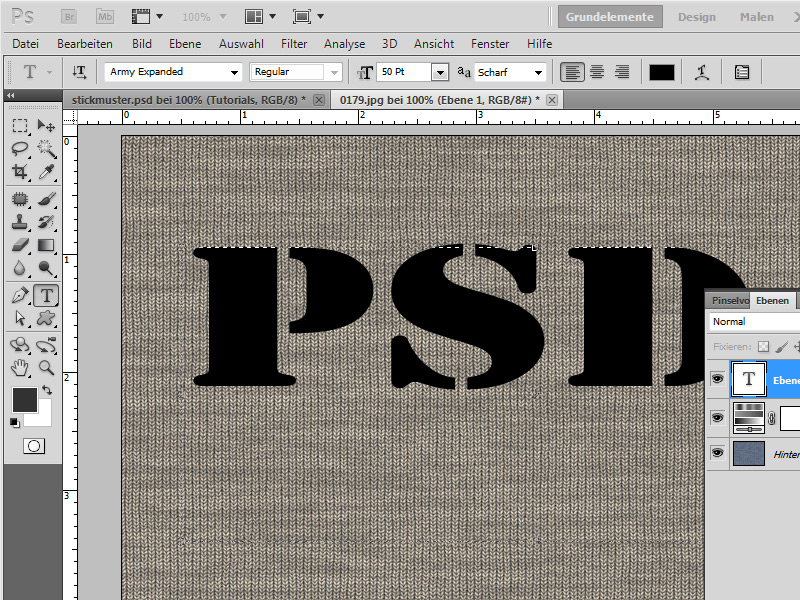
Mit Strg und Klick auf die Ebenenminiatur meiner Textebene wähle ich die Buchstaben aus. Nun wähle ich das Pfade-Bedienfeld und klicke dort auf das Icon Arbeitspfad aus Auswahl erstellen.
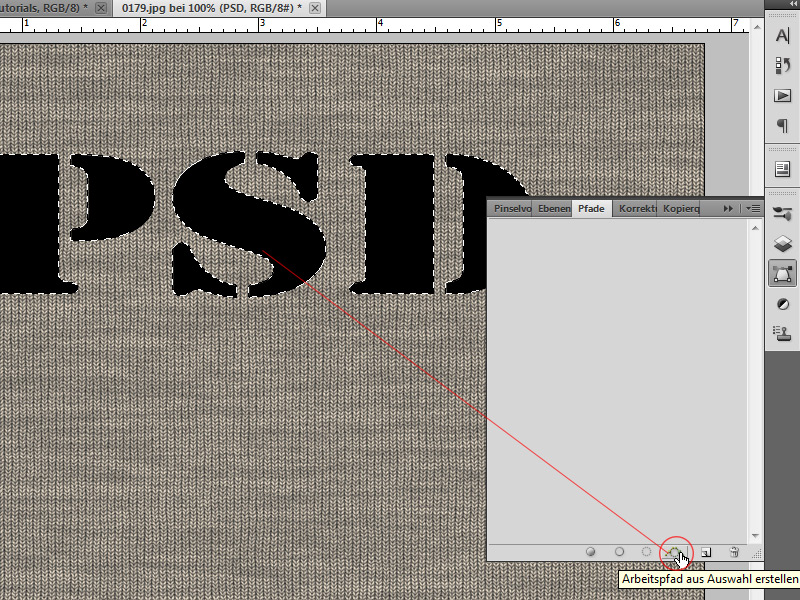
Nun kann ich meinen Arbeitspfadkontur mit einem Brush füllen. Notwendig ist, dass dazu mein Pinselwerkzeug aktiviert ist und ich einen passenden Stickmuster-Brush als Pinselvorgabe im Repertoire habe.
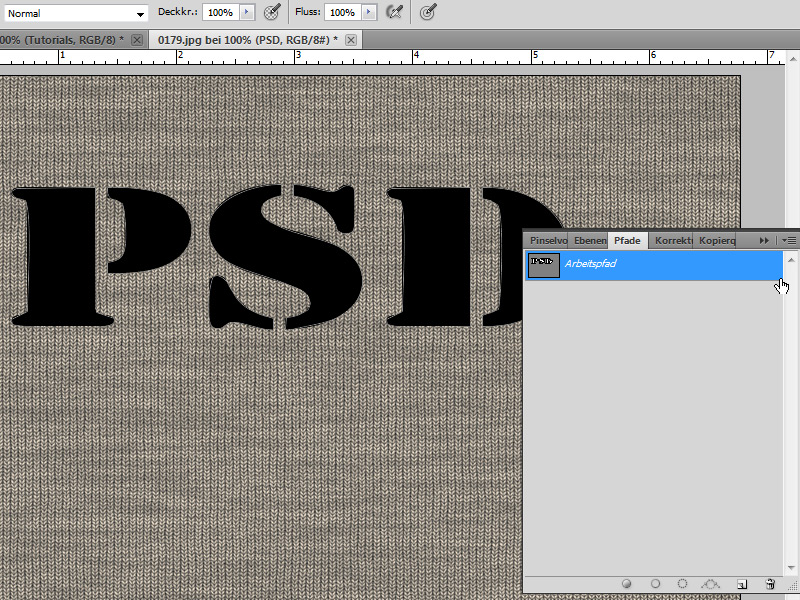
Ich erstelle ein neues Dokument mit dem Shortcut Strg+N. Das neue Dokument hat die Größe 50×50.
Mit Strg+Shift+Alt+N erstelle ich eine neue Ebene. Die Hintergrundebene kann ich ausblenden, sodass der Hintergrund transparent ist.
Um die Pinselvorgabe ordentlich in das Dokument zu zeichnen, zoome ich auf ca. 500 Prozent. Ich wähle einen runden harten Pinsel und zeichne damit einfach ein „V“ in mein neues Dokument. Wichtig: Beim Einzeichnen bitte darauf achten, dass das „V“ nicht den Rand berührt. Sonst gibt es später beim Brushen harte, unschöne Kanten.
Anschließend kann ich mit Strg und Klick auf die Ebenenminiatur meiner V-Ebene das V auswählen und über das Menü Bearbeiten>Pinselvorgabe festlegen als neue Pinselspitze speichern.
Es geht zurück in das ursprüngliche Dokument. Mit dem Shortcut F5 öffne ich das Pinsel-Bedienfeld. Das Pinsel-Werkzeug B wird aktiviert. In den Vorgaben finde ich jetzt meine zuvor festgelegte Pinselspitze.
Ich wähle eine Größe von 12 Pixeln bei einem Abstand von 84 Prozent.
In den Formeigenschaften stelle ich unter Winkel-Jitter bei Steuerung: Richtung ein. Diese Einstellung sorgt dafür, dass die Fortführung des Pinselauftrags auch bei Kurven und Ecken richtig dargestellt wird.
Ich erstelle eine neue Ebene mit dem Shortcut Strg+Shift+Alt+N. Der Farbton der Vordergrundfarbe ist ein helles Grau (90 Prozent Helligkeit).
Die neu erstellte Ebene ist aktiviert. Ich ruf mein Pfade-Bedienfeld auf und wähle das Icon Pfadkontur mit Pinsel füllen.
Und schon hat mein Text eine gestickte Kontur.
Damit das Stickmuster auch ordentlich wirkt, passe ich den Look noch ein wenig in den Fülloptionen der Ebene an.
Schlagschatten:
• Deckkraft: 30 Prozent
• Abstand: 1 Pixel • Überfüllen: 0 • Größe: 0
Abgeflachte Kante und Relief:
• Stil: Abgeflachte Kante innen
• Technik: Abrunden
• Tiefe: 100 Prozent
• Größe: 0
• Weichzeichnen: 0
• Schattierung: Standardeinstellungen, bei beiden 75 Prozent
Jetzt hat die gestickte Kontur auch noch einen leichten Schlagschatten, sodass sie ein wenig plastischer ausschaut.
Vorweg: Eine Jeanstextur gibt es bereits als Mustervorgabe in Photoshop. Ich rufe zu meiner Textebene die Fülloptionen auf und wähle dort Musterüberlagerung. Im Untermenü rufe ich Muster 2 auf.
Dort finde ich eine fertige Jeanstextur.
Um ein wenig mehr Freiheiten im Feintuning der Texturoptik zu haben, kann ich die Jeanstextur auch sehr einfach selbst erstellen. Denn die Mustervorgabe von Photoshop ist äußerst klein (64x64px) – wenn auch kachelbar – und kann nur über Umwegen akzeptabel in der Erscheinung verändert werden.
Ich erstelle eine neue Datei mit dem Shortcut Strg+N. Die Größe des Dokument ist 800x800px. Die Hintergrundebene fülle ich mit einem mittleren Blau (3c5695).
Dann lege ich eine neue Ebene mit dem Shortcut Strg+Shift+N an. In dem sich öffnenden Dialogfenster wähle ich unter Modus Weiches Licht und aktiviere die Checkbox für ein 50-prozentiges Grau. Im Farbwähler stelle ich mit dem Short D die Standardfarben ein.